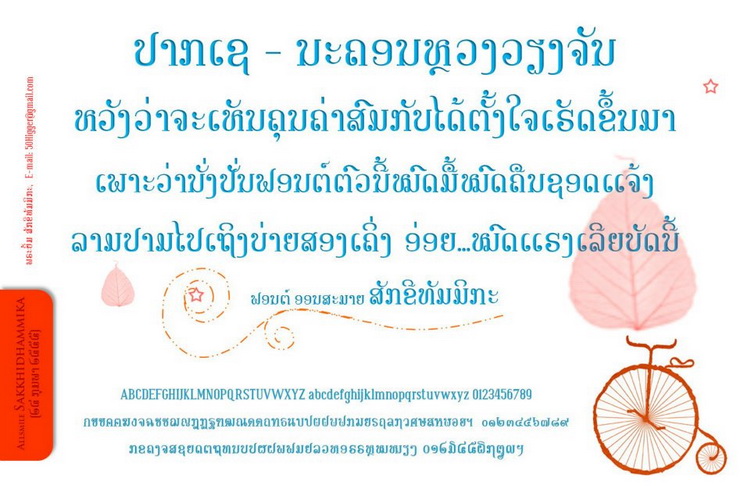
Alsmile Golden Class
:25: เยี่ยมเลย (ภาษาอังกฤษคุ้นๆ)
อักษรลาวแบบแฟนซีๆ นี่มีไหมครับ
(ภาษาอังกฤษมันคุ้นเพราะว่า ปรับให้ตัว R มันคล้าย พี่เฮลวา ตัวปัญหาที่ทำให้คนททะเลาะกันนั่นละ  :15: :30:)
ทำไมจะไม่มี ทำการปรับเป็นภาษาลาวแล้วเรียบร้อย ตัวข้างล่างนี้ไง
จะให้ Nixona ปล่อยเร็ว ๆ นี้ละ แต่มันมีปัญหาสระลอยแค่นั้นเอง แก้ไม่เป็น
สุดยอด :07: กรี๊ดดดดดดดดดดดด
ฟอนต์ตัวนี้มีแค่ภาษาลาวเท่านั้นนะครับ ไม่มีไทยไม่มีอังกฤษไม่สามารถทำ Unicode ได้
แล้วที่พากันชื่นชมนี่ พวกโยมพี่ทั้งหลายอ่านภาษาลาวกันออกหรอครับ หรือแค่เห็นรูปแบบก็บอกว่าเจ๋ง สุดยอด ห๊ะ :43:
เดี๋ยวจะสานต่อเทมเพลตลาวไทยอังกฤษให้เป็นเทมเพลตที่ใช้ให้จงได้
โยมพี่ท่านไหนที่จะช่วยกรุณาเดี๋ยวรอชี้แนะละกันนะครับ
ถ้าพยายามก็พอจะอ่านออกครับ :05:
แอบไปทำฟอนต์ลาว-ไทย-ฝรั่ง อีกตัว(ทั้งที่ทำงานวิจัยไม่เสร็จ คิคิ)
เอามาลงให้ดู ยังไม่เสร็จสมบูรณ์ เหนื่อยมาก แต่ก็ภูมิใจมาก
ตัวละตินออกแบบไม่เสร็จ แต่คิดว่าจะเป็นใน Concept นี้ (เอาของฝรั่งมาดูเป็นต้นแบบ)
ฟอนต์ลาวออกแบบให้แปลกมากไม่ได้ กระทรวงวัฒนธรรมดูแลอยู่ ทำได้แค่นี้
ดูออกไหม.... :30: :30: :30: